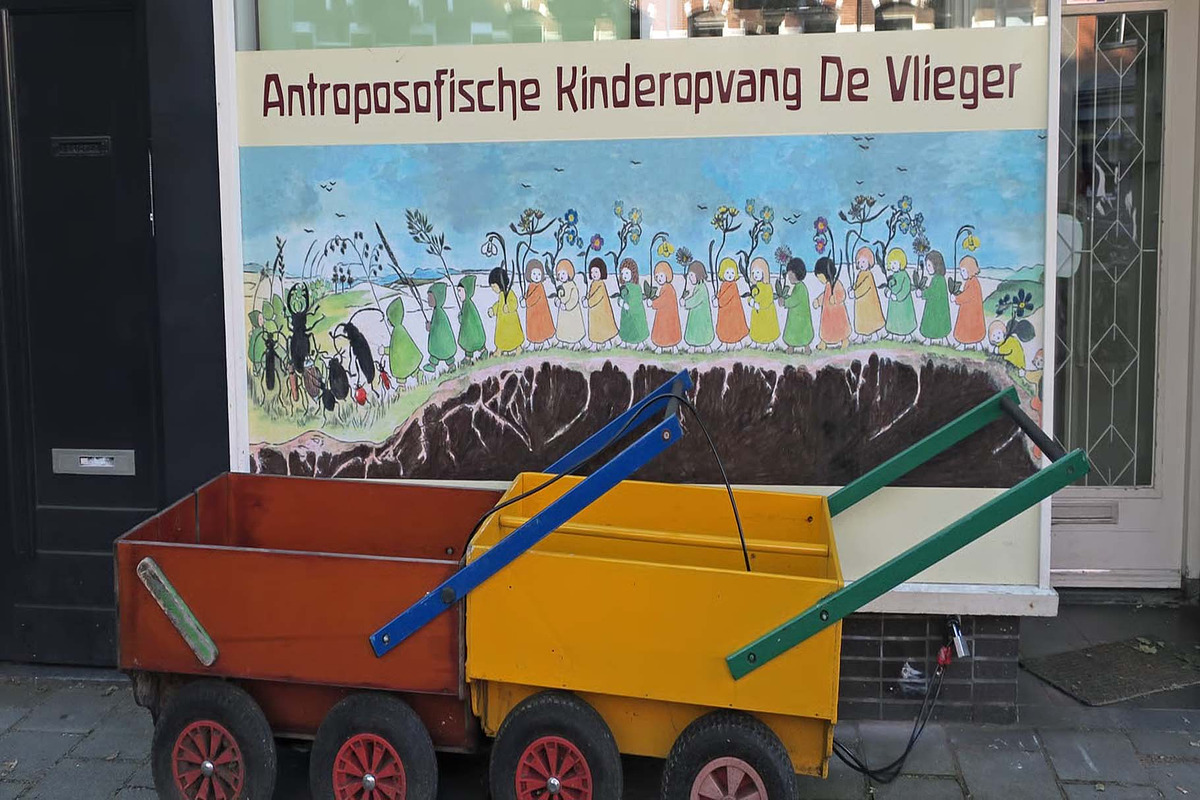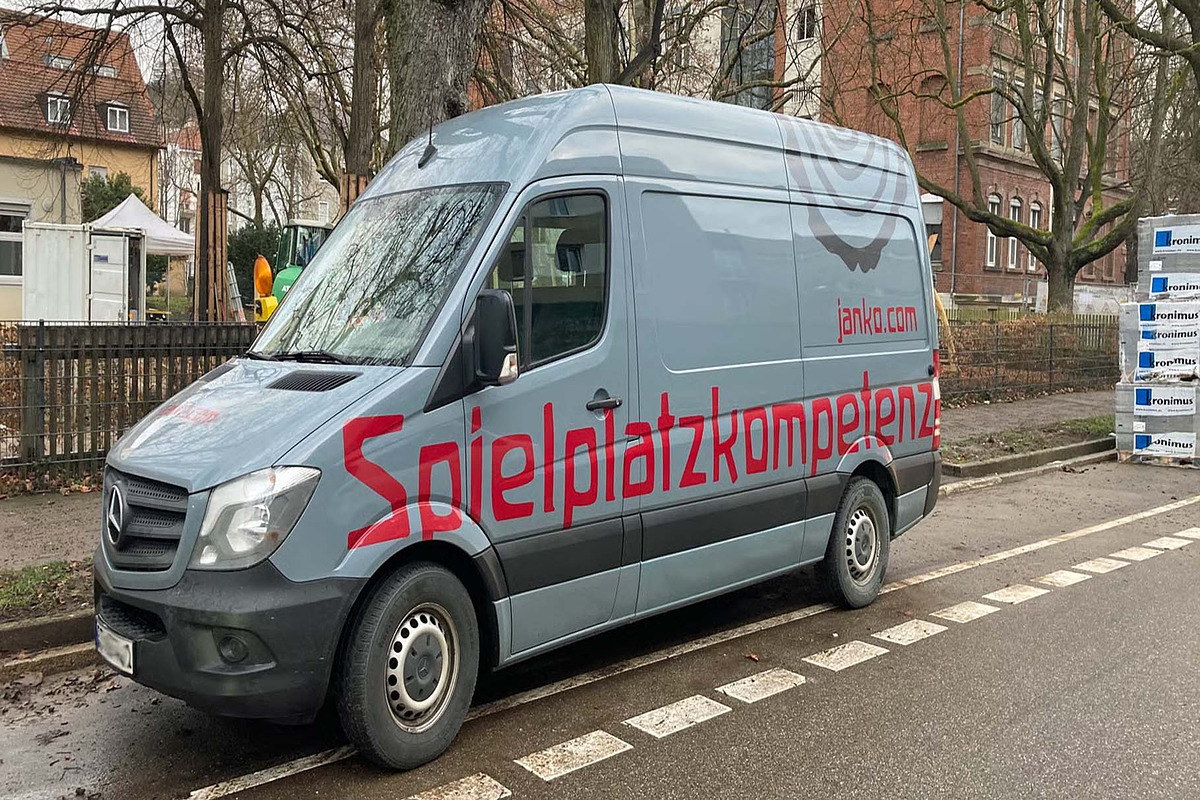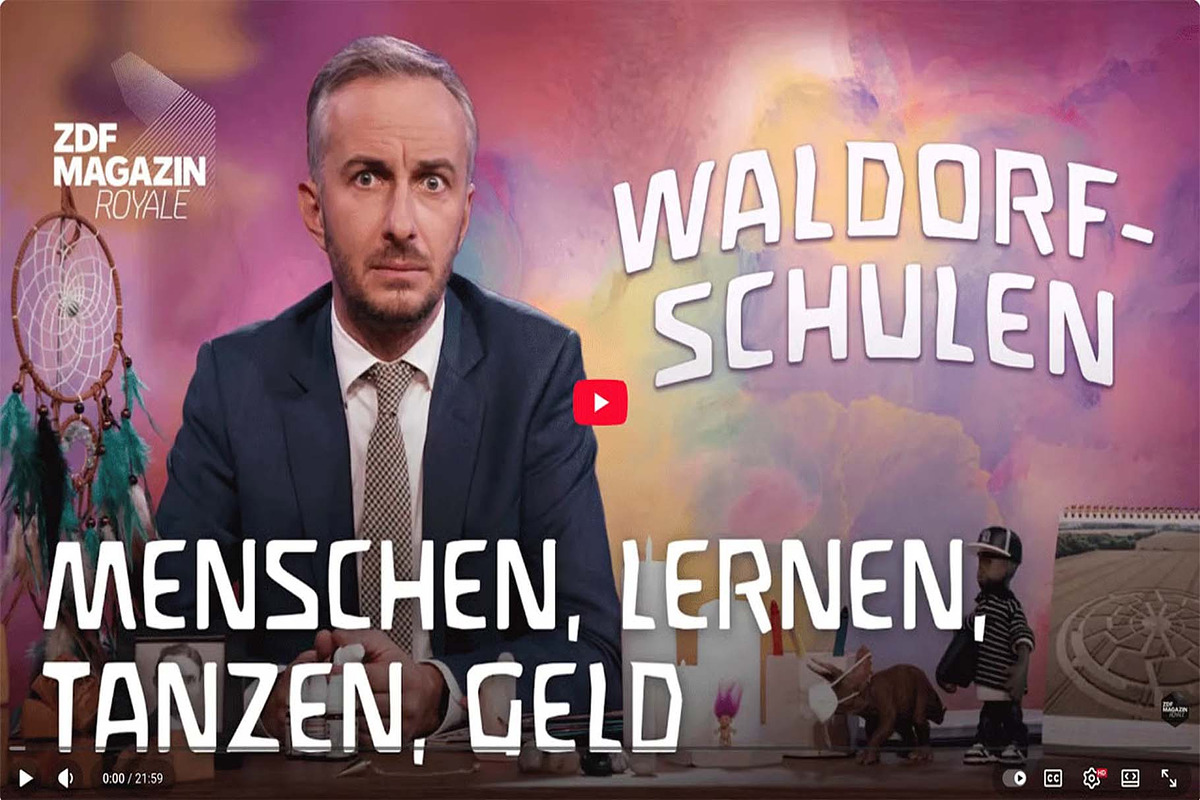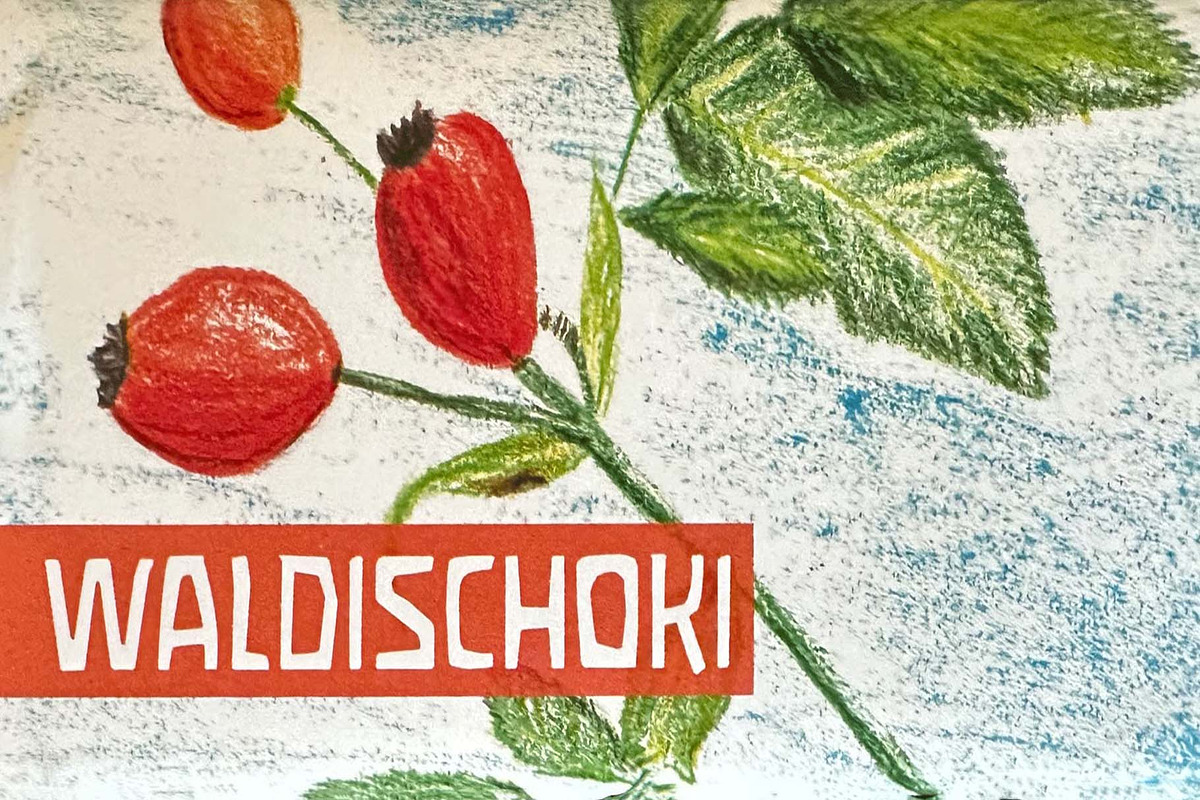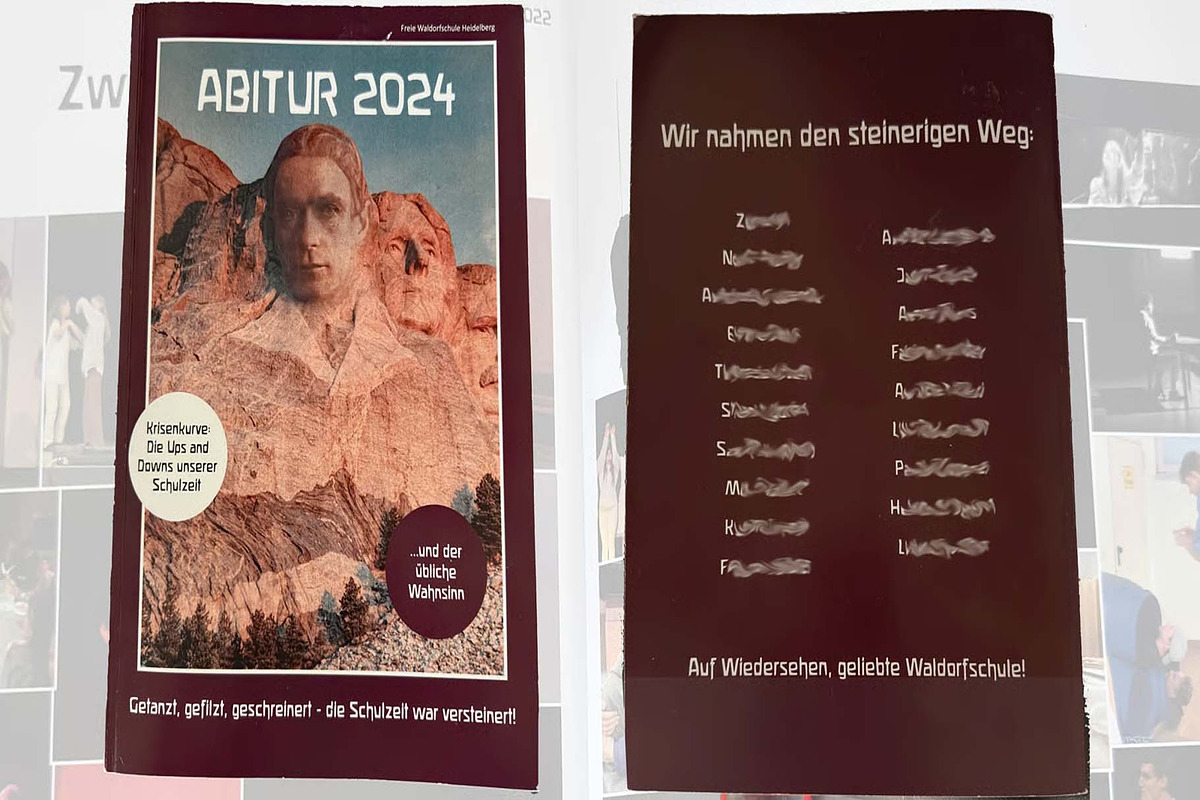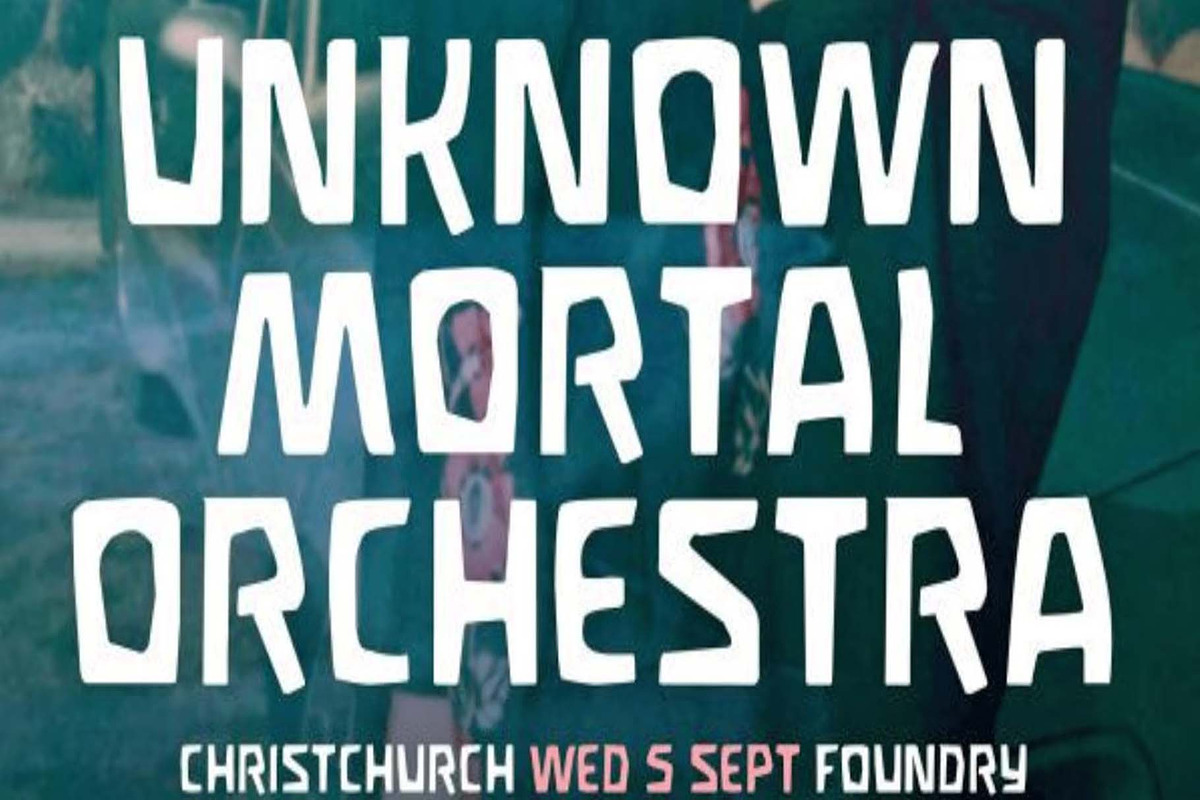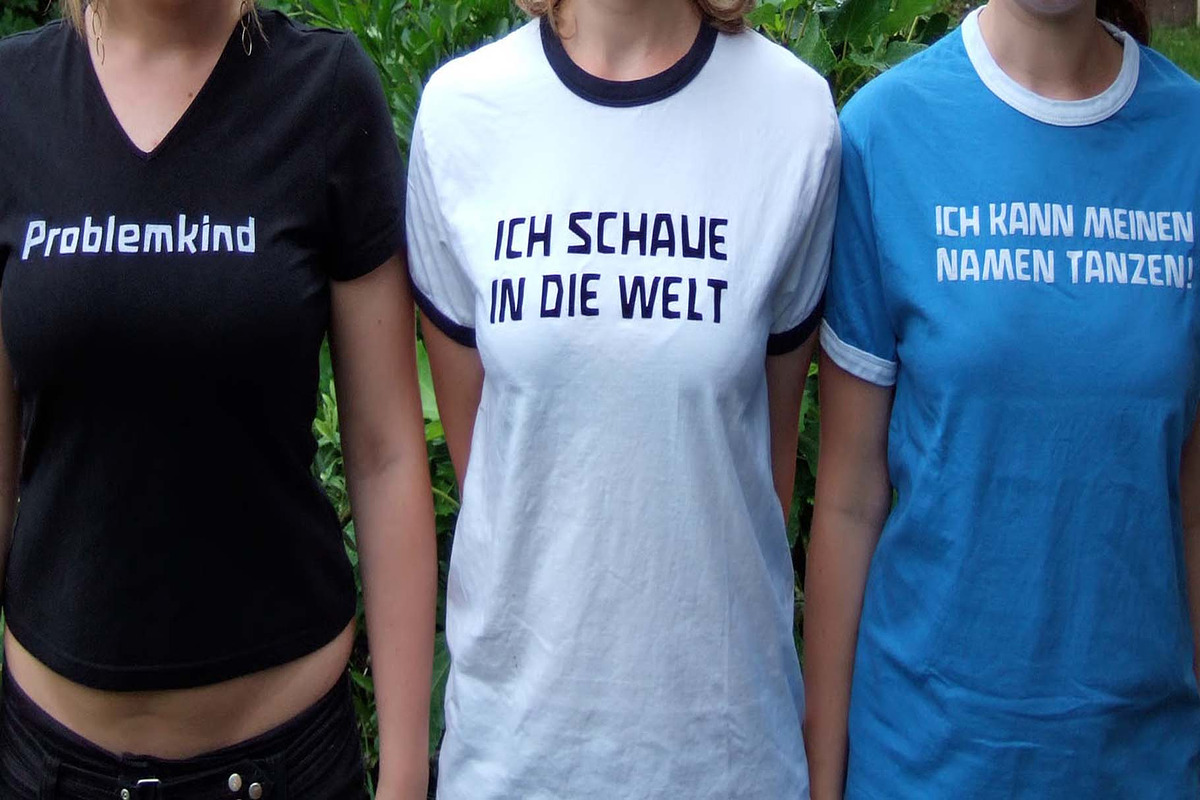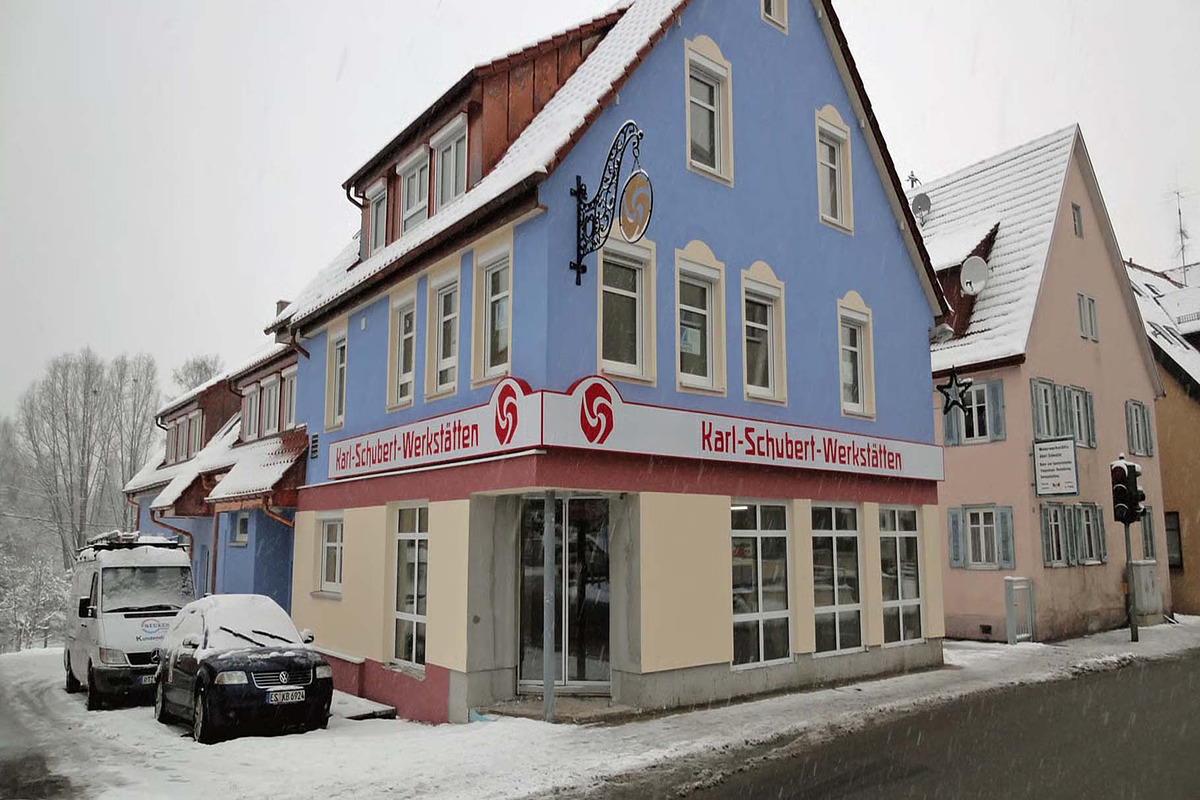
Waldorfschrift
Die Waldorfschrift-Familie wurde in den Jahren 1993-1994 von Joachim Frank in digitaler Form erstellt, inspiriert von den naturgemäß organischen Briefen aus der anthroposophischen Bewegung des 20. Jahrhunderts von
Rudolf Steiner
. In der Natur gibt es keine rechten Winkel, keine geraden Linien und keine völlige Gleichförmigkeit, sondern runde Ecken, unterschiedliche Dicken und alle Arten von Variabilität. Das ist es, was die
anthroposophische Bewegung
in ihren Gebäuden, ihrer Kunst, ihrer Musik - und auch in ihrer Schrift.
Und diese Schrift ist wie die Pflanzen in der Natur: sie wächst in die Höhe, verzweigt sich, Buchstaben schmiegen sich an manche, zu anderen halten sie mehr Abstand, manche Buchstaben recken stolz ihren Bauch, andere kauern in der Ecke - eine ganz natürliche Schrift. Werfen Sie einen Blick auf die Marke von
Weleda
(das Naturkosmetikunternehmen),
Demeter
(eines der größten Unternehmen für ökologische Lebensmittel),
Filderklinik
(ein großes anthroposophisches Krankenhaus in Deutschland) und Sie werden sehen, dass diese großartigen Unternehmen mit unterschiedlichen, aber organischen Buchstabenstilen arbeiten. In jüngerer Zeit hat Joachim die Waldorf-Schriften mit moderner Schriftgestaltungssoftware überarbeitet und zusätzliche Zeichen wie das Euro-Zeichen und zusätzliche Strichstärken hinzugefügt, um die Schriften für eine Vielzahl von Gestaltungsaufgaben nutzbar zu machen.